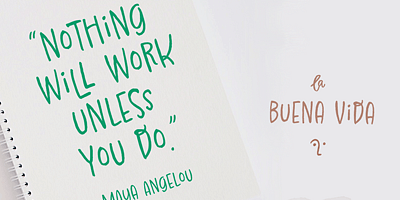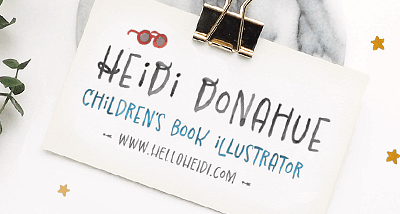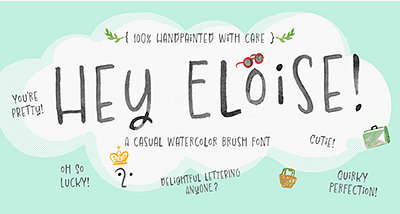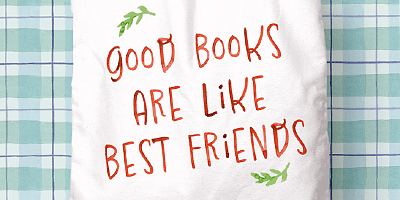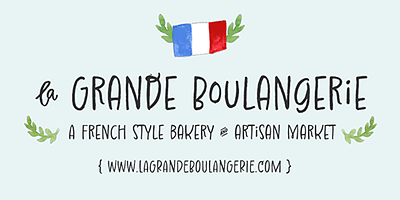
Hey Eloise est une police à casse unique créée à la main avec un pinceau et de l’encre. Elle est disponible dans des variations de style gouache solide ou aquarelle. Facile à personnaliser, vous pouvez basculer entre les jeux de caractères en activant et désactivant le verrouillage des majuscules ou en sélectionnant des glyphes individuels via les fonctionnalités Opentype.
Caractéristiques : ligatures standard et discrétionnaires, variantes de glyphes, fractions et glyphes bonus, mots clés décoratifs.